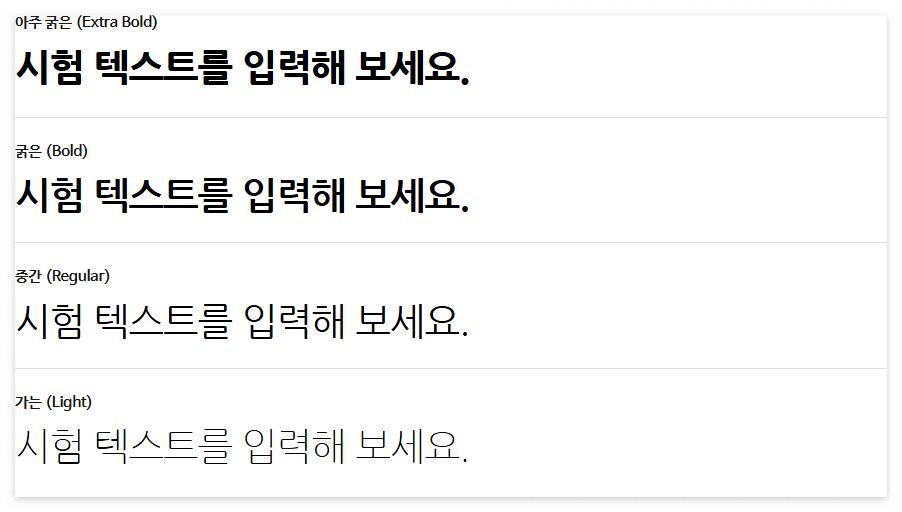
나눔고딕은 네이버가 제공하는 무료 폰트로, 단순히 무료라는 점을 넘어 기능성과 심미성을 동시에 만족시키는 서체입니다.
현대적 감각과 가독성을 갖춘 이 글꼴은 문서 작업, 웹디자인, 그래픽 작업 등 다양한 분야에서 사랑받고 있습니다.
나눔고딕의 특징과 장점
나눔고딕은 단순한 글꼴이 아니라 작업의 품질을 높이는 도구입니다.
다음은 나눔고딕이 가진 주요 장점입니다.
1. 다양한 굵기로 활용 범위 확대
나눔고딕은 Extra Bold, Bold, Regular, Light의 네 가지 굵기를 지원합니다.
이는 제목부터 본문까지 다양한 용도로 활용할 수 있는 가능성을 열어줍니다.
| 굵기 옵션 | 활용 방안 |
|---|---|
| Extra Bold | 포스터 제목, 광고 문구 등 강조 |
| Bold | 서브 제목, 문서의 하이라이트 |
| Regular | 문서 본문, 긴 텍스트 작성 |
| Light | 미니멀한 디자인, 웹디자인 요소 |
굵기 선택이 자유롭기 때문에 다양한 디자인 프로젝트에서 유연하게 사용 가능합니다.
2. 뛰어난 가독성
글자 끝부분의 날카로운 모서리를 둥글게 처리한 나눔고딕은 부드럽고 친근한 느낌을 제공합니다.
이는 긴 텍스트를 읽을 때 피로감을 줄여주는 효과가 있어 문서 작성과 발표 자료에서 특히 유용합니다.
3. 폭넓은 문자 지원
나눔고딕은 한글 11,172자, 한자 4,888자, 영문 94자, KS 약물 986자를 지원합니다.
이는 한글 문서뿐만 아니라 다국어 콘텐츠에서도 유용하게 쓰일 수 있다는 의미입니다.
특히 다량의 문자 세트를 활용해야 하는 프로젝트에서 큰 강점을 발휘합니다.
나눔고딕의 활용 방안
1. 문서 작성과 보고서 디자인
가독성이 뛰어난 나눔고딕은 기업 보고서, 제안서, 프레젠테이션 슬라이드 등 문서 작성에 최적화되어 있습니다.
Regular 굵기로 본문을 작성하고, Bold 또는 Extra Bold로 제목과 강조 문구를 작성하면 깔끔하면서도 명확한 인상을 줄 수 있습니다.
2. 웹디자인 및 UI/UX 디자인
웹디자인에서는 가독성이 가장 중요합니다.
나눔고딕은 웹 폰트 URL과 CSS를 통해 쉽게 적용할 수 있으며, Light와 Regular 굵기는 미니멀하고 세련된 웹디자인에 적합합니다.
3. 그래픽 디자인
광고 포스터, 배너, 명함 등 그래픽 디자인에서도 나눔고딕은 활용도가 높습니다.
특히 Extra Bold 굵기는 타이포그래피 디자인에서 강렬한 첫인상을 남기는 데 적합합니다.
4. 교육 콘텐츠 제작
교육 자료나 e러닝 콘텐츠에서도 나눔고딕은 큰 효과를 발휘합니다.
어린이부터 성인까지 누구나 쉽게 읽을 수 있는 가독성을 제공하므로, 다양한 연령층을 타깃으로 한 콘텐츠에 적합합니다.
나눔고딕 사용 후기
나눔고딕은 무료 폰트이면서도 유료 서체에 뒤지지 않는 높은 품질을 제공합니다.
문서 작업에 활용할 때는 깔끔한 인상을, 웹디자인에서는 현대적인 감각을, 그래픽 작업에서는 강렬한 메시지를 전달하는 데 효과적입니다.
실제로 나눔고딕을 사용해본 사용자들은 이 폰트가 프로젝트의 완성도를 높여준다고 말합니다.
문서 작업에서는 Regular와 Bold의 조화로 명료한 문서를 제작할 수 있었고, 그래픽 디자인 작업에서는 Extra Bold의 강렬함으로 강조 효과를 톡톡히 보았습니다.
가독성과 활용성이라는 두 마리 토끼를 모두 잡은 서체라는 점에서, 사용자 만족도가 높은 폰트로 평가받고 있습니다.
마치며